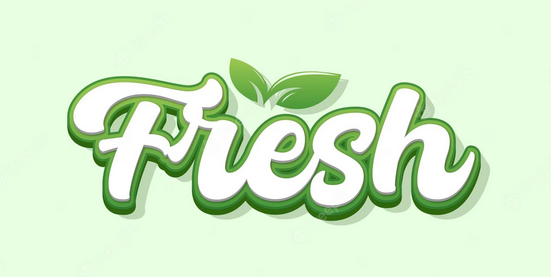
Änhliche Schrift für Frisch, Anregend, Belebend
ich suche vom Stil her eine ähnliche, für privat kostenlose, Schrift. Sie sollte "massiv" (keine Outlines). Die Schrift möchte ich für das Wort "Erfrischend" (Frisch, Anregend, Belebend) benutzen. Nicht unbedingt nur körperlich, sondern auch geistig. Da sie für ein Poster über anderen Schriften liegt, sollte sie mittelfett bis fett sein. Gerne natürlich auch andere Ideen.
Die Calafia (Neil Secretario, 2017) geht mehr in Richtung Flachpinsel-Schildermaler-Schrift, hat aber einen tollen Rhythmus und ist auch »erfrischend«.